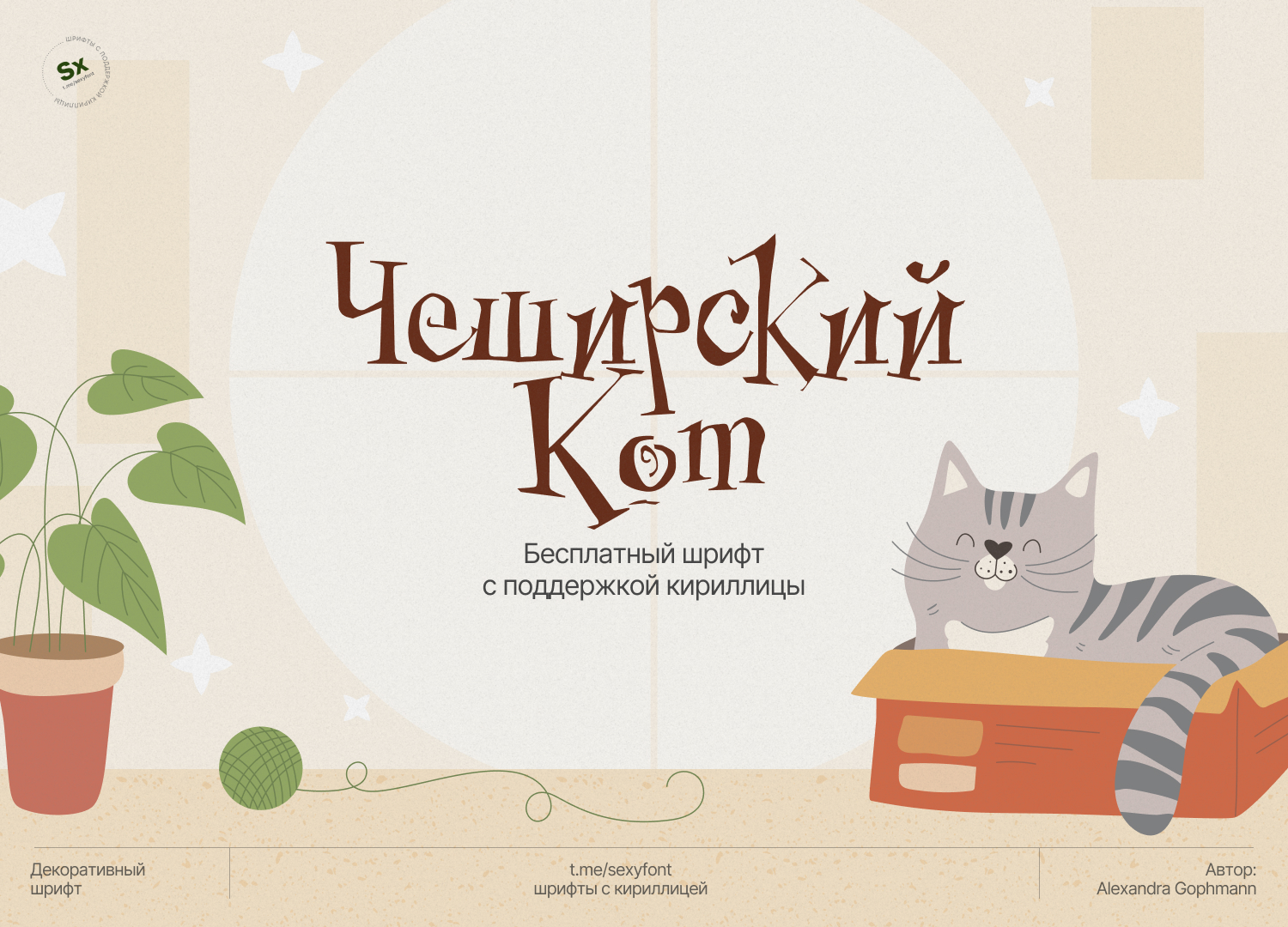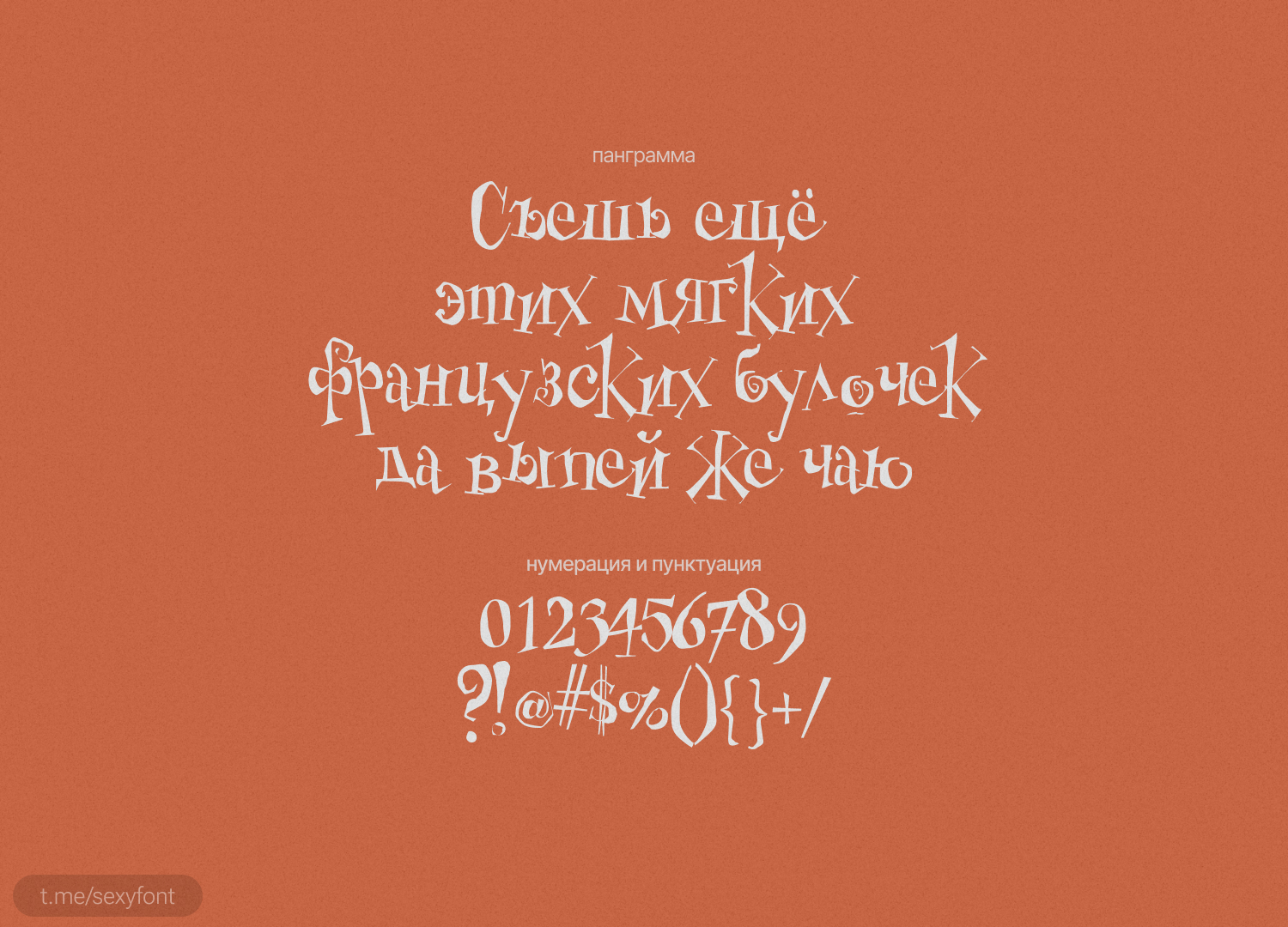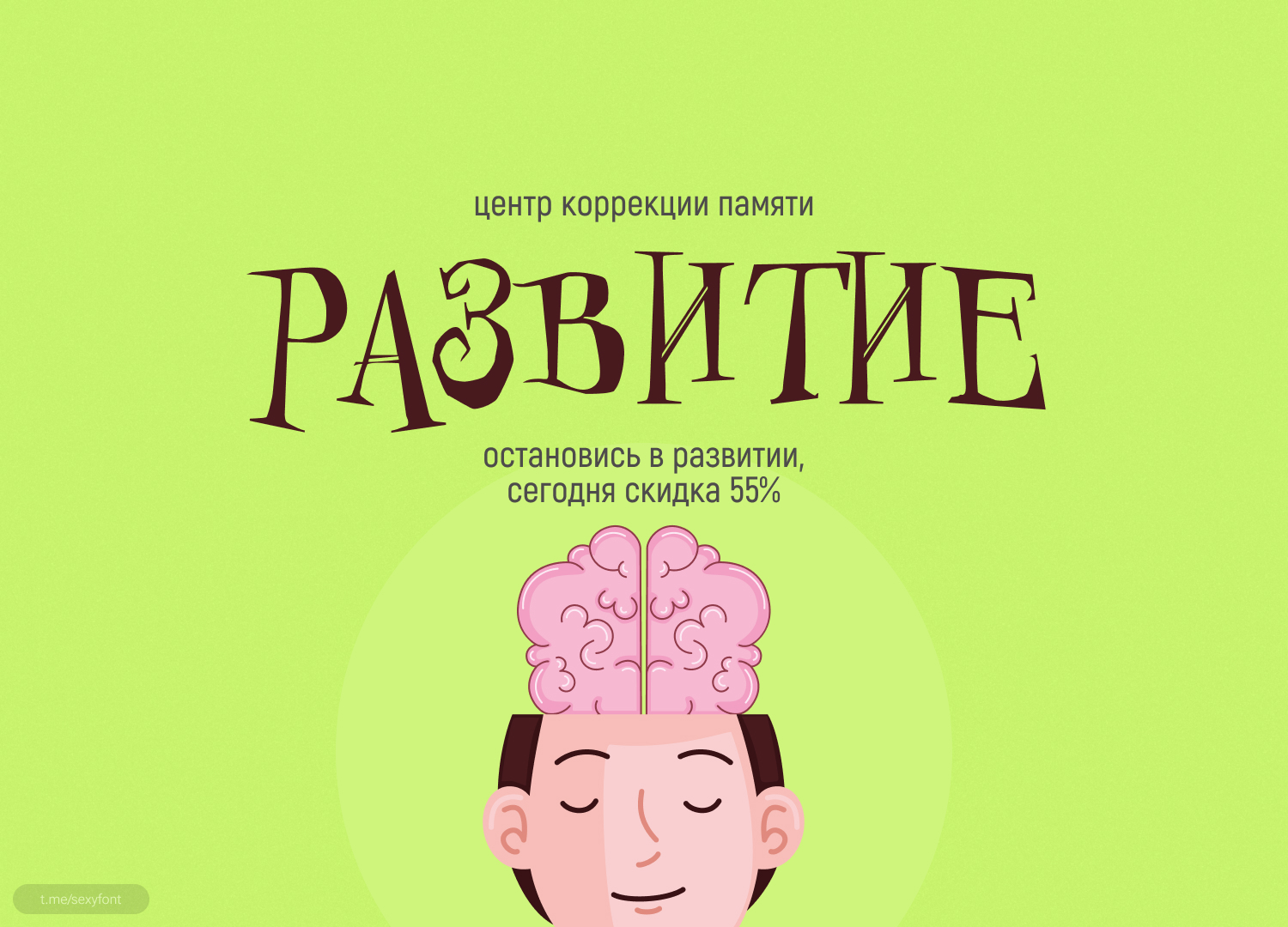
Бесплатный шрифт Cheshirskiy Cat
Мяу! Новая презентация. Cheshirskiy Cat. Чеширский Кот. Декоративный шрифт с характером. Буквы пляшут, закручиваются и немного дерзят. Идеально для всего сказочного: детские книги, кондитерские, упаковка, афиши.Автор - Alexandra Gophmann.